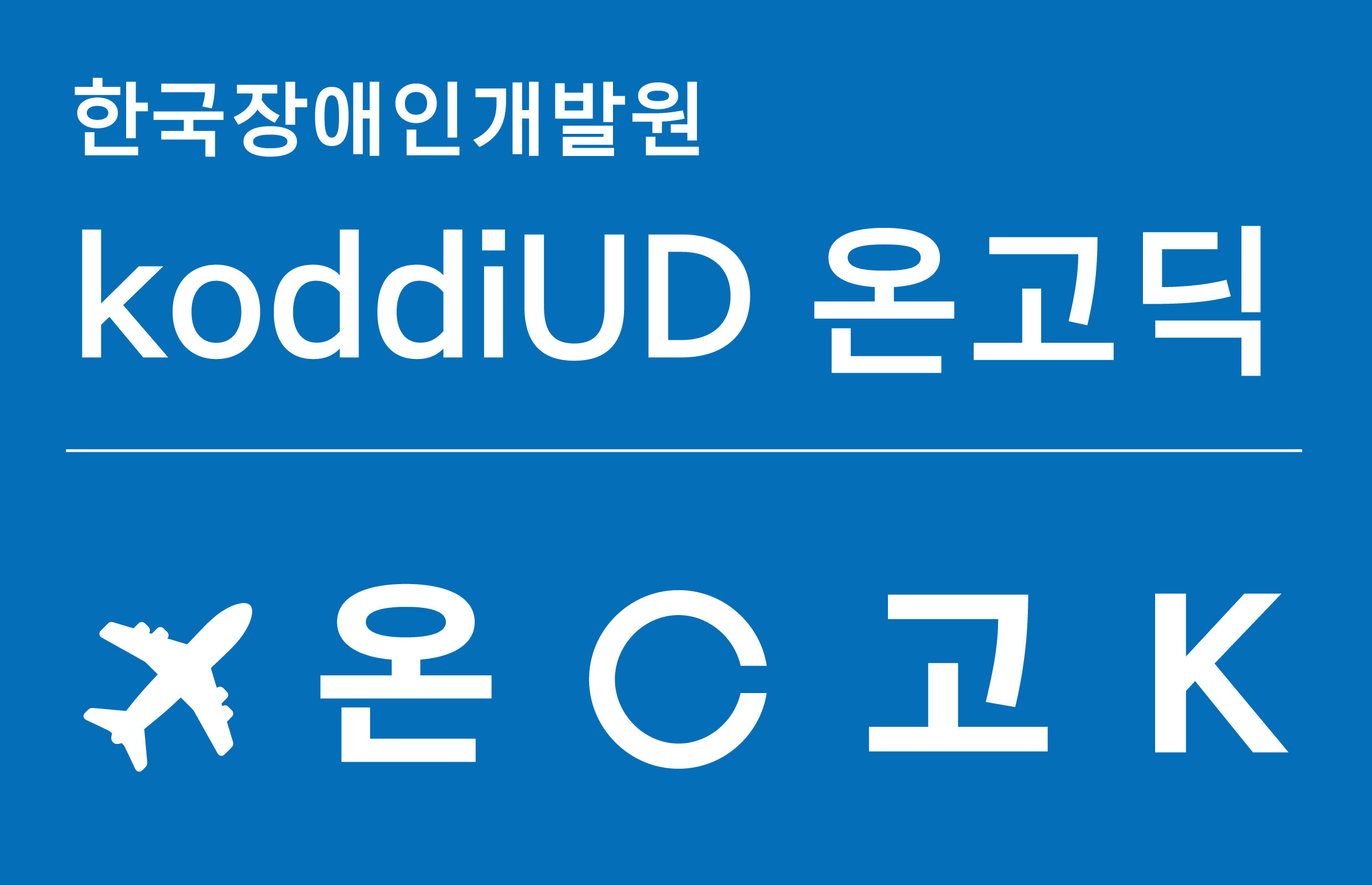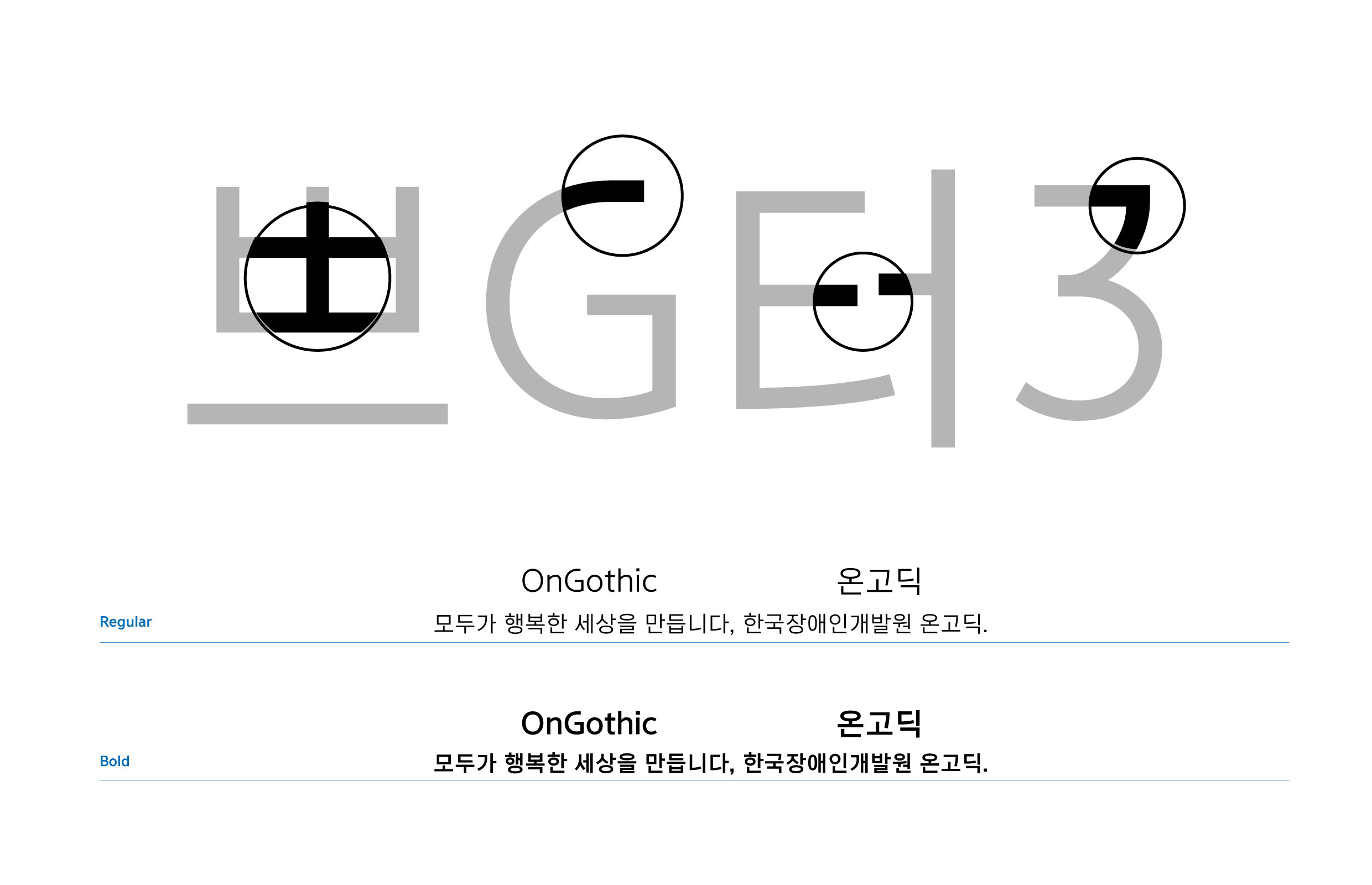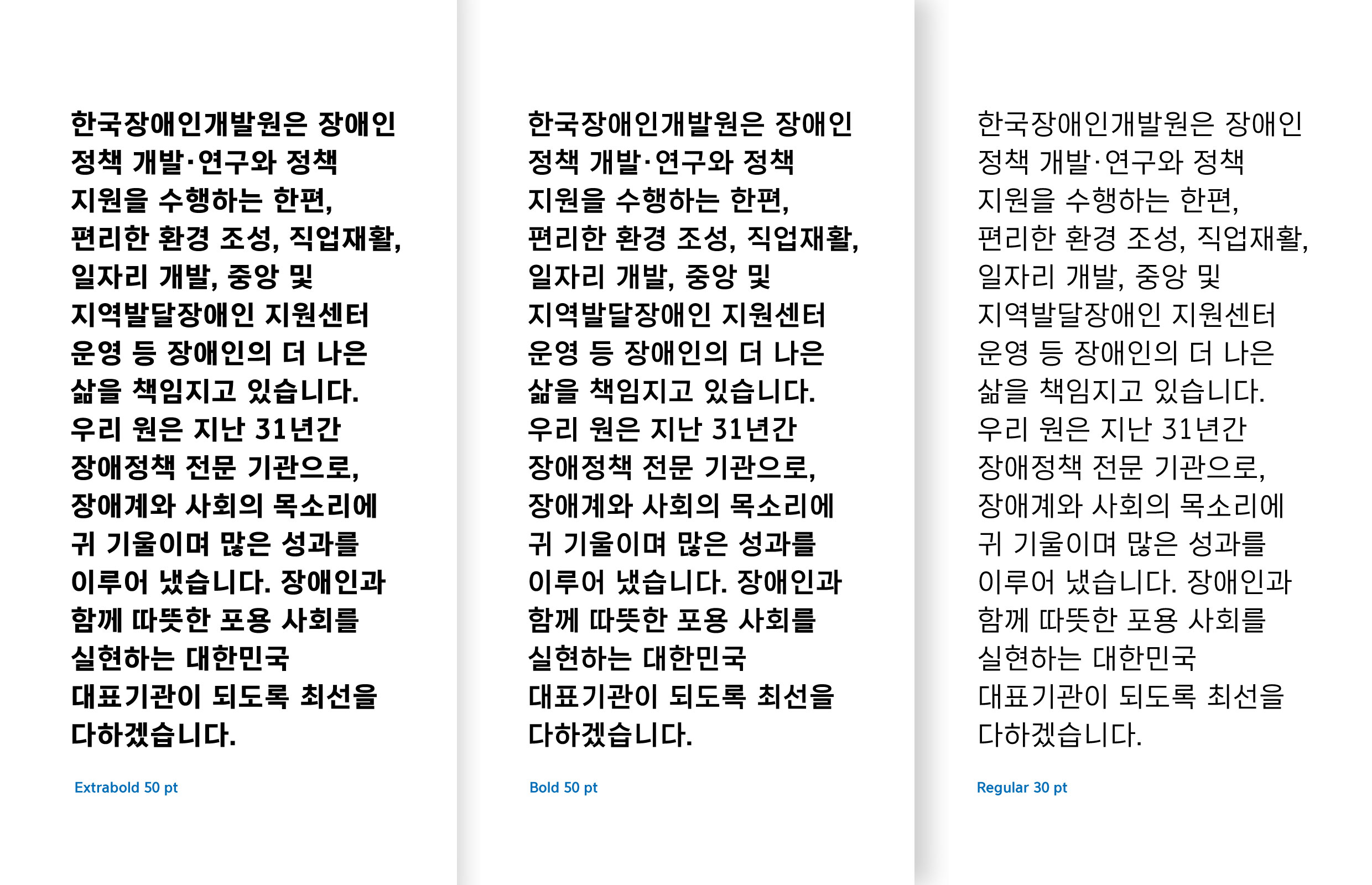
한국장애인개발원
2020 이후
KoddiUD 온고딕 서체는, 10~70대 332명을 대상으로 글꼴 테스트를 진행-기존의 고딕 서체를 분석하고 오독의 여지가 높고 인지 상의 문제가 있는 글자들을 미리 연구-한 후, 작은 글자 등 열악한 글자 상황에서도 판독의 문제가 없도록 디자인된 유니버설(Universal Design) 서체다.
KoddiUD 온고딕 Regular, Bold, Extra Bold
윤디자인그룹
이정은, 박현준